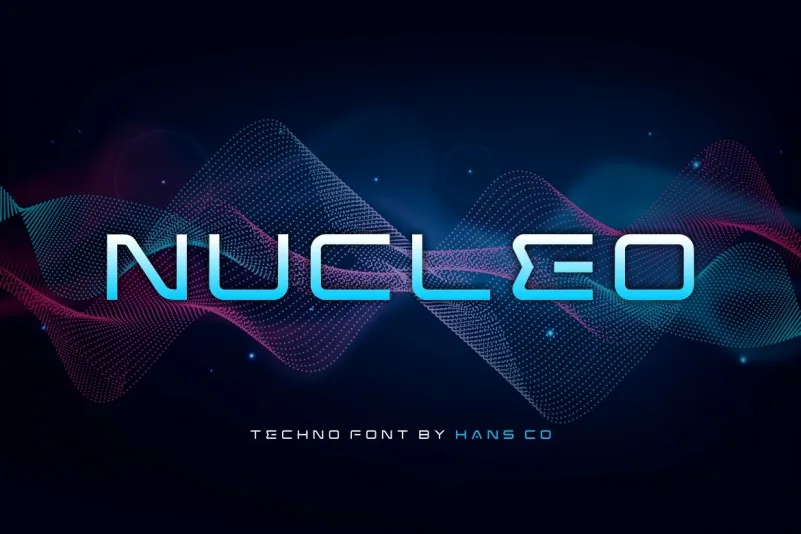
A Nucleo Font é uma tipografia sans-serif que oferece um visual limpo e futurista perfeito para projetos visionários. Com seu estilo moderno e minimalista, ela traz uma sensação de elegância a qualquer projeto que exija essa delicadeza clara. Essa fonte surge como uma excelente adição à coleção de fontes, oferecendo um toque contemporâneo sem perder o encanto do design simples. Em um mundo onde os elementos futuristas estão cada vez mais presentes em nossa vida cotidiana, a Nucleo Font se destaca por sua capacidade de capturar essa energia com uma aparência moderna e limpa, tornando-a perfeita para qualquer projeto que busque uma elegância minimalista.